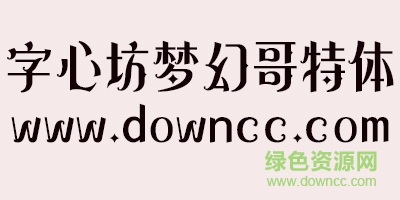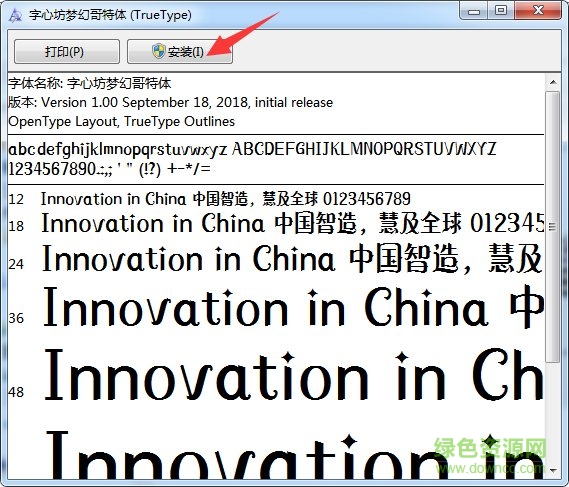
字心坊夢幻哥特是一個富有詩情畫意的電腦字體。可以用于設(shè)計(jì)書籍、海報(bào)、游戲等字幕。字體適用范圍廣。如果您需要字心坊夢幻哥特字體的話可以直接在本站免費(fèi)下載安裝。
字體風(fēng)格:
哥特風(fēng)/華麗/時(shí)尚
推薦場景:
標(biāo)志/導(dǎo)視/書籍/游戲/動漫/影視/屏顯
字心坊夢幻哥特體是一款免費(fèi)的哥特風(fēng)字體,字體獨(dú)特,新穎華麗。漢字藝術(shù)與西方文字的融合,如夜空中閃爍著暗黑光芒;個性鮮明的字體特征,散發(fā)著神秘而高冷的氣息。在華麗而不失婉約中,感受哥特風(fēng)的魅力。